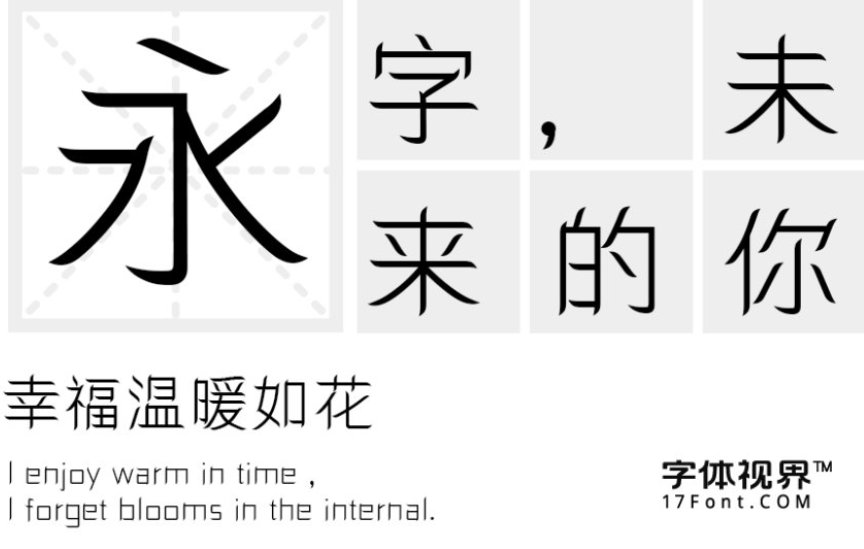
三极细柳简体发布
字体名称:三极细柳简体
字体类别:创意字体
三极细柳简体简介:三极细柳简体是一款非常优秀好用的艺术设计方面的中文简体创意字体,整体风格轻巧简洁,笔画飘逸、平直,粗细匀称,起笔收笔为柳叶状,折、钩转折明显,细节刻画鲜明。它的灵感来源于柳叶,弱柳扶风,江水初平。给人一种温暖亲切,干净利落的感觉,具有婉约柔和的气质。视觉效果字体方正稳健又有柳叶的飘荡动感,实用性强。
三极细柳简体预览图展示: